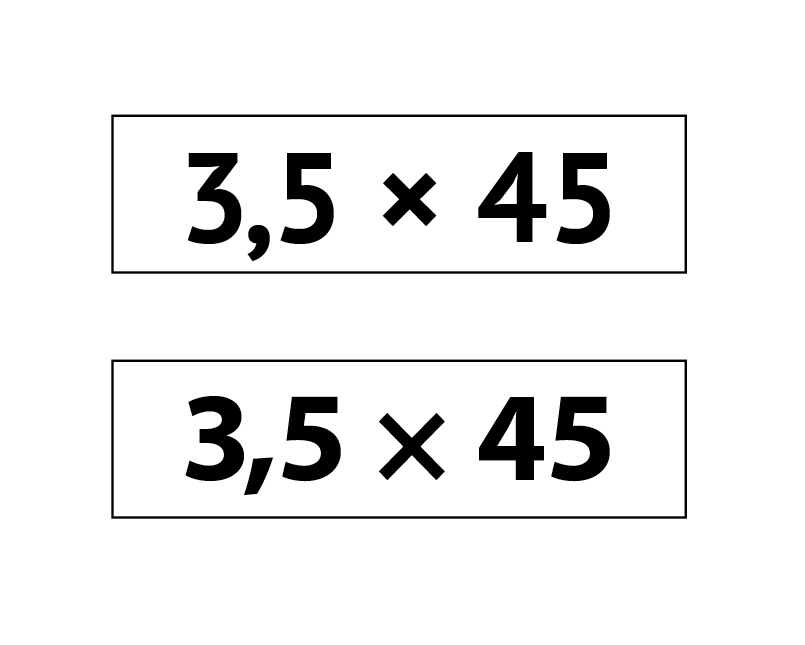
Schraubensortiment etikettieren (bei wenig Platz: 17 mm × 4,6 mm)
Ein Freund mit einem umfangreichen Schraubensortiment bat mich, dieses mit Hilfe meines Etikettendrucker zu beschriften.
Mein eigenes Schraubensortiment in kleinen maßgefertigten kleinen Pappkartons beschrifte ich mit 'nem weichen Bleistift :)
Rund um die Typografie zu Ziffern habe ich mir noch kaum Gedanken gemacht und würde mich über Euren Rat/Eure Inspiration freuen.
Die Etiketten sind 6 mm breit und 21 mm lang. Das ist gegeben und kann nicht verändert werden.
Die Minimalränder des Etikettendruckers sind 2 mm links und rechts und 0,7 mm oben und unten.
Somit ergibt sich eine bespielbare Fläche von 17 mm × 4,6 mm.
Die Beschriftung besteht aus je einer Angabe zum Durchmesser und zur Länge.
Die Durchmesser sind in Schritten von 0,5 mm gestuft.
Beispiele:
3 × 30
3,5 × 30
3,5 × 35
3,5 × 40
4 × 30
4 × 35
4,5 × 40
4,5 × 45
Experimentiert habe ich mit dem Verkleinern der Nachkommastelle inklusive des Kommas auf 7pt und Normalgewicht (bei einem Schriftgrad 12pt und fettem Gewicht beim Rest).
Weiterhin habe ich statt des "×" das Zeichen "·" eingesetzt.
3,5 · 45
Welche Schriftart, welches Gewicht findet ihr toll für solche Zwecke?
Die Auflösung des Druckers (Brother 1230PC) beträgt nominell 180dpi.
Die Kernfrage ist "Zurücknehmen der Nachkommastelle?" und wenn ja, wie am besten.
Das Zurücknehmen der Nachkommastelle macht in meinen Augen wenig Sinn, da sie wesentlicher Bestandteil der Maßangabe ist. Ebenso würde ich das „ד nicht durch „·“ ersetzen, da es die beiden Maße trennt. In deinem Beispiel lese ich 3,5 und 45 anstelle von 3,5 mal 45 mm.
Ich würde auf eine (schmale) humanistische Grotesk setzen, wie beispielsweise die Bernini von Tim Ahrens.
Das Zurücknehmen der Nachkommastelle macht in meinen Augen wenig Sinn, da sie wesentlicher Bestandteil der Maßangabe ist.
Es geht mir um das schnelle und leichte Erfassen von Gruppen aus dicht beieinanderliegenden Durchmessern.
Meinem Auge jedenfalls fällt dies sehr viel leichter, wenn die Nachkommastelle gegenüber der Ganzzahl zurückgenommen wird.
Wenn ich mich richtig erinnere, habe ich das auch in wissenschaftlichen Arbeiten und technischen Beschreibungen schon gesehen.
Es dient (dort) auch der Verhütung von Fehlern, wo statt "3,5" falsch "35" gelesen wird.
Ebenso würde ich das „ד nicht durch „·“ ersetzen, da es die beiden Maße trennt. In deinem Beispiel lese ich 3,5 und 45 anstelle von 3,5 mal 45 mm.
Das "·" ist ein gängiges Symbol für ein Malzeichen.
Zur Bernini: Wie nennt man eigentlich das Gestaltmerkmal eines horizontalen Fußes an der "1"?
Welche Schriftart, welches Gewicht findet ihr toll für solche Zwecke?
Eine schmalhalbfette Egyptienne, wie z. B. die Technotyp.
Das "·" ist ein gängiges Symbol für ein Malzeichen.
Für die Schrauben scheint mir das x spontan auch passender als das · .
Hochstellen wäre eine Alternative, die es bspw. bei den zwei führenden Ziffern der Gau-Krüger-Koordinaten an Koordinatengittern auf klassischen topographischen Karten gibt:
3456 für den Rechtswert und 5430 für den Hochwert bspw. von meiner Ecke ... die drei fehlenden nachfolgenden Ziffern für die vollständigen Koordinaten muss man dann mit Lieal und Dreisatz aus dem Gitter ablesen ...
Ich meine, ich hätte Hochstellungen auch schon mal für Nachkommastellen gesehen bzw. für "halbe" Werte, also bei zwei Nachkommastellen die 3. Stelle als 5, wenn in Maßangaben angegeben wird, dass da noch ein halber Zentimeter dazu kommt ...
Die Nachkommastelle zu verkleinern scheint mir auch nicht unüblich:
... und hat mich beim Schraubensuchen im Baumarkt auch noch nie wirklich gestört. Gerade wenn eine Größe auf dem nächst tieferen Regal weiter geht gucke ich zur groben Orientierung auf die erste Zahl, dann auf die Nachkommastelle und dann auf die Länge.
Ich würde mir einfach keinen zu großen Kopf machen und die beiden Angaben Durchmesser und Länge irgendwie voneinander trennen, beispielsweise 3,5 • 45 oder 3,5 × 45 oder 3,5 x 45 oder 3,5—45 oder … eigentlich völlig egal, weil es ja immer nur um die beiden Maße Durchmesser und Länge geht. Einzig das schnelle Erfassen ist ausschlaggebend.
Die hoch- oder tiefgestellte 5 als halber Wert kann auch gut funktionieren, weil es außer bei sehr kleinen Feingewindeschrauben nur halbe mm als Wert gibt. Wichtiger wäre mir da auch die Angabe der Festigkeitsklasse, wenn ich nicht grad lauter 8.8-Baumarktschrauben verwende.
Hochstellen wäre eine Alternative
Bei der zur Verfügung stehenden sehr geringen Höhe des Etikettes leider nicht. Dann müsste man zwingend einen kleineren Schriftgrad verwenden. Und für den Zwecke will man den größten Schriftgrad, der nicht dazu führt, dass die maximale Breite bei den unterzubringenden Inhalten überschritten wird.
Es ist eine Aufgabe. Kein Problem.
Dir steht es natürlich frei meine bisherigen Überlegungen als Verschlimmbesserung zu bewerten.
Deine Argumentationsfigur "Es geht nicht um etwas Hochrangiges wie ein Leitsystem" passt nicht zu einem Forum, wo alle sich freiwillig an einer Debatte beteiligen können oder nicht.
Mir macht es jedenfalls Spaß, Gestaltmöglichkeiten und ihre Auswirkungen auf die Erfassbarkeit auch bei so einem kleinen Ding auszuloten.